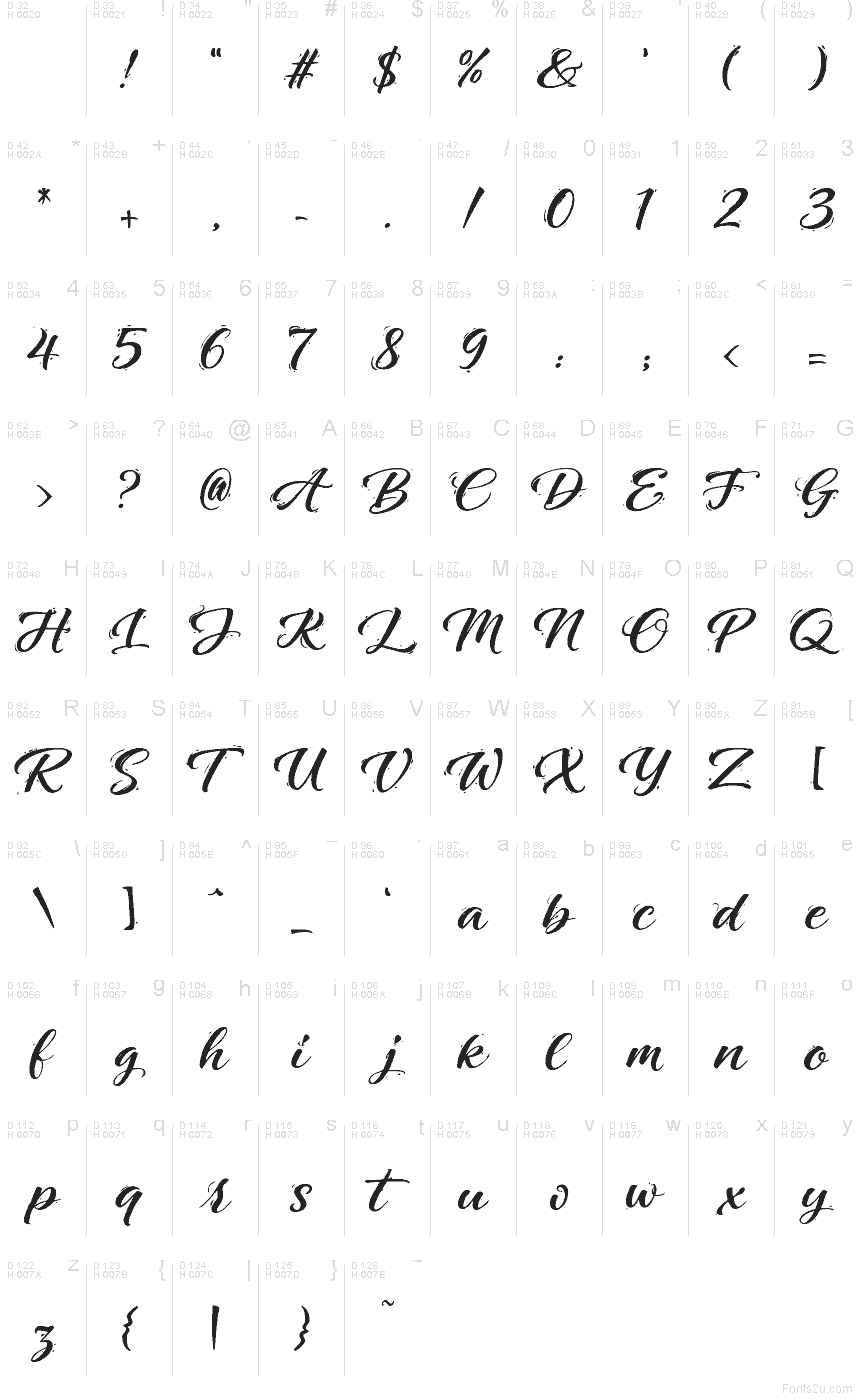
Tropical Cocktail od BlackFridayFont je bezplatné kaligrafické skriptové písmo s výrazným kontrastem silných a tenkých tahů a naddimenzovanými ozdobnými prvky. Dlouhé náběhové tahy, smyčková spojení a živé změny směru dodávají nápisům teatrální rozmáchlost. Drobné mezery a zdrsněné okraje narušují jinak plynulý průběh tahů.
Obzvláště příhodné uplatnění najde při tvorbě vizuální identity koktejlových barů, ačkoli jeho splývavé křivky skvěle vyniknou i na pozvánkách na akce, módních obalech nebo hudebních plakátech. Ve všech těchto případech kaligrafické tahy přirozeně proměňují jména a titulky v součást dekorativní grafiky.